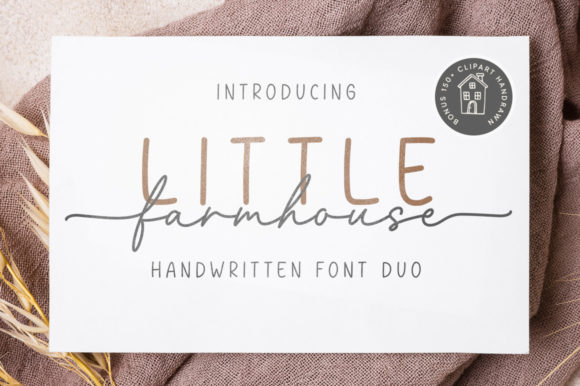
Little Farmhouse
適切なデザイン要素を見つけるのは難しい場合がありますが、Little Farmhouseは作品を即座に引き立てる優れたコレクションを提供します。
POD(オンデマンド印刷)製品、結婚式の招待状、またはソーシャルメディアのグラフィックを作成している場合でも、Little Farmhouseは理想的です。